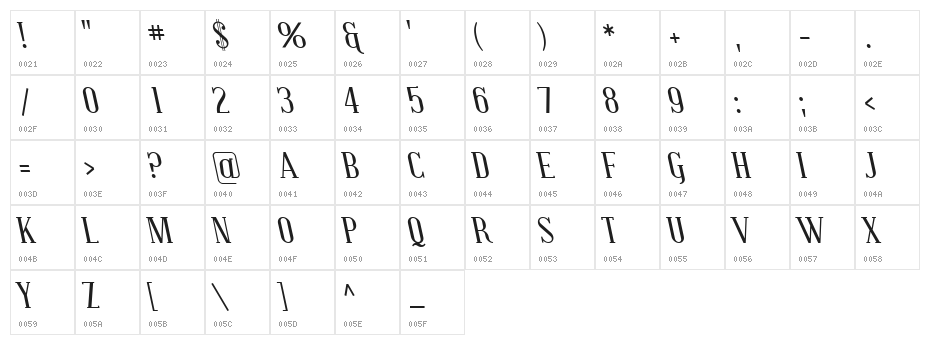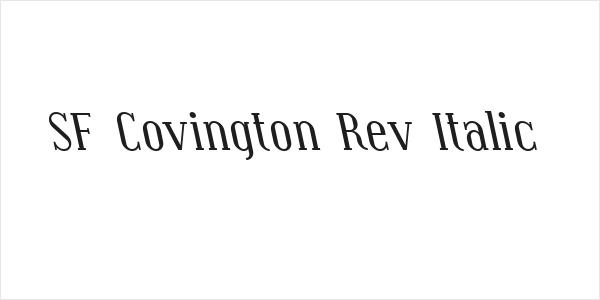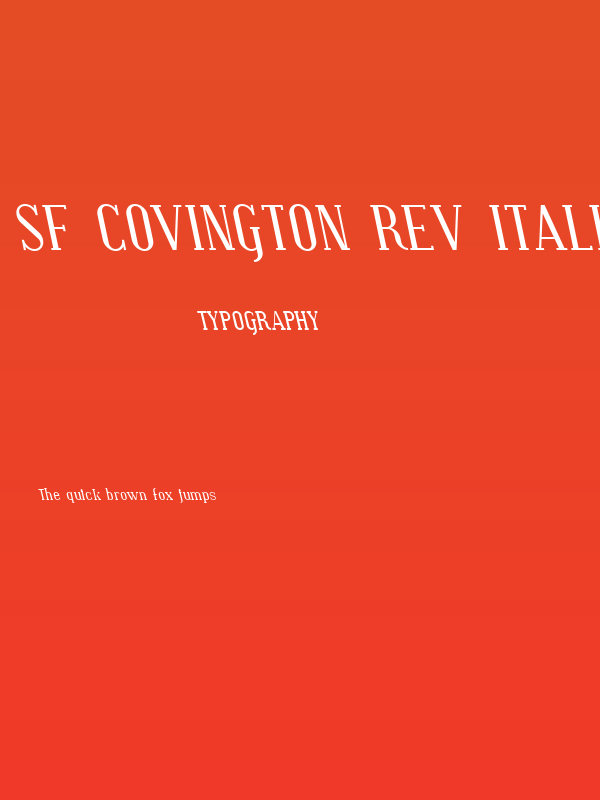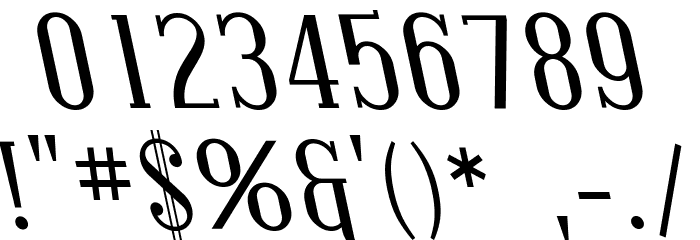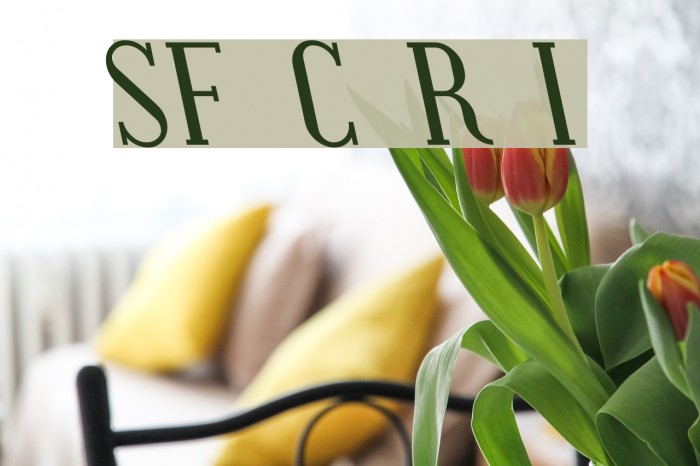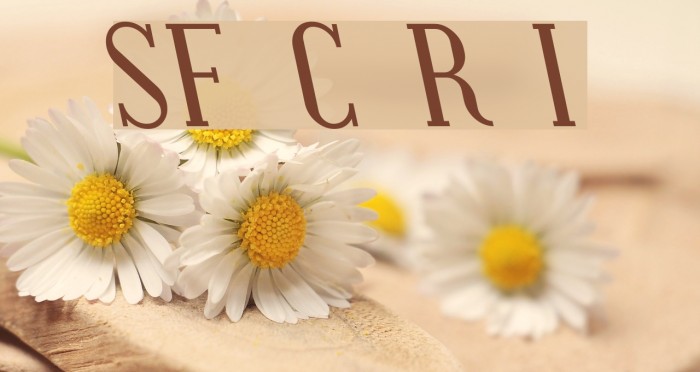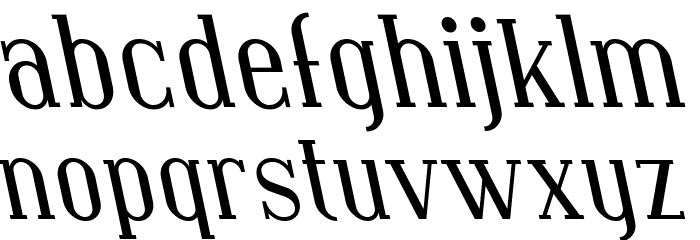
SF Covington Rev Italic Font
| Progetti proposti | Ideal for editorial design, book covers, formal invitations, and branding materials that require a touch of sophistication. |